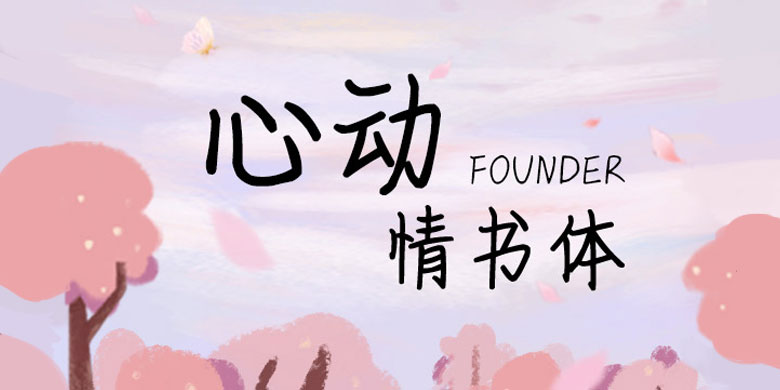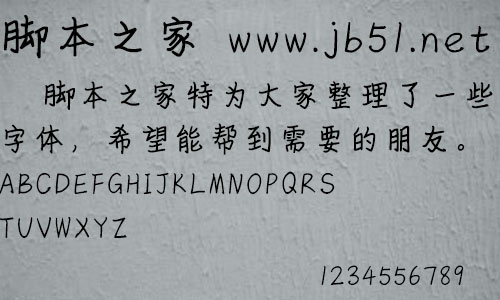
方正手跡-心動(dòng)情書體由方正字庫余丹設(shè)計(jì)師出品的藝術(shù)字體,字體筆觸適中,字形充滿青春活力,適合應(yīng)用于藝術(shù)設(shè)計(jì)、平面宣傳設(shè)計(jì)、網(wǎng)頁設(shè)計(jì),書法等領(lǐng)域。
心動(dòng)情書體有別于傳統(tǒng)的楷書,它給人們的感覺更多的內(nèi)斂含蓄,而又有從容不迫的韻律感。適用于文藝類的書刊、品牌廣告和產(chǎn)品包裝設(shè)計(jì),以及社交網(wǎng)絡(luò)的個(gè)性化用字。。。